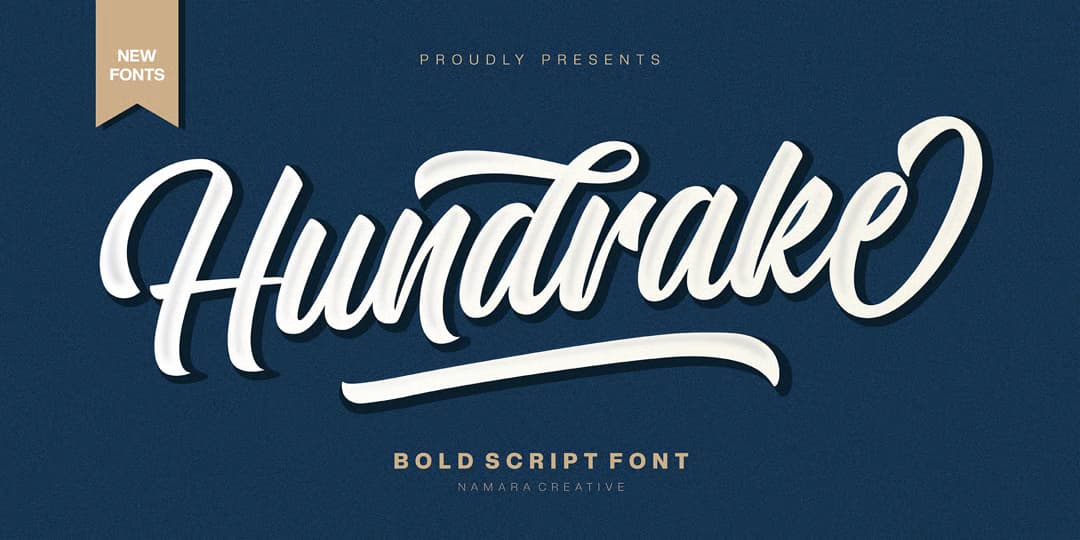
Hundrake
レトロアメリカンテイストのレタリングスクリプト。太めのブラッシュスクリプトを模したレタリングによるスクリプトで、ミッドセンチュリー感のあるボテっとした風合いが特徴。ちょっとしたスワッシュが付いたオルタネートが大量にあり、手書きとは逆の左向きのストロークが多いのがレタリングの面目躍如という所である。リガチャーもちょこちょこあり。異次元の活躍を見せるオオタニサンに敬意を評し、メジャーでもよく見るこのタイプのスクリプトを紹介してみた。